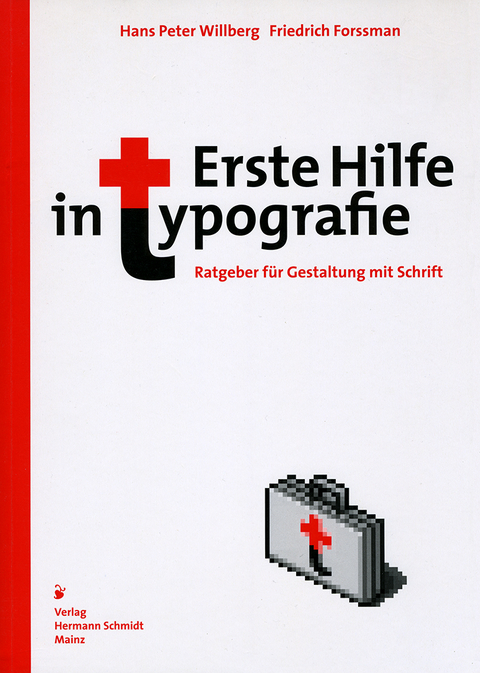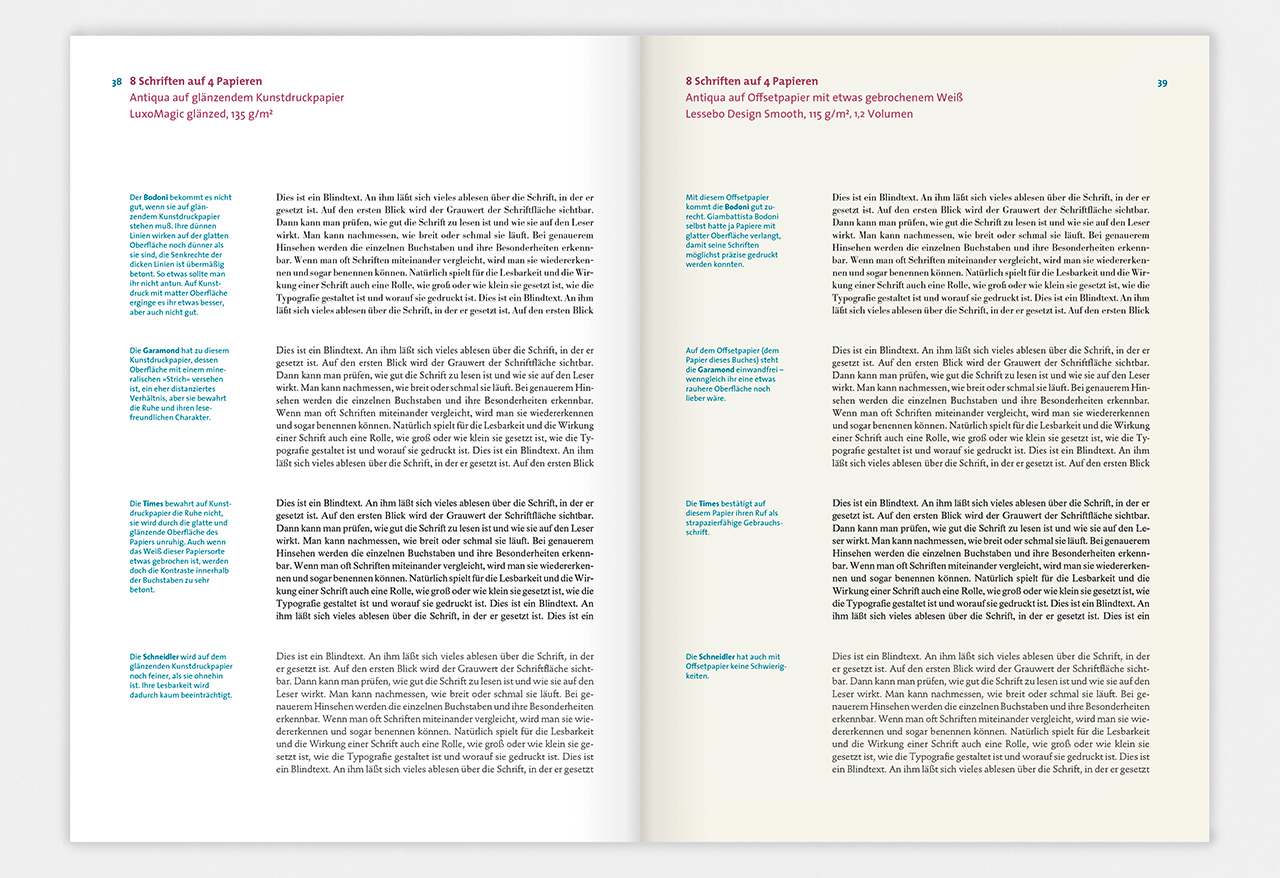
Erste Hilfe in Typografie
Ratgeber für Gestaltung mit Schrift
Jeder, der am Computer einen Text erfasst, gibt ihm eine Form. Bewusst, gekonnt, unbewusst oder ungekonnt, wir setzen ihn in Szene – und interpretieren ihn. Nicht immer – und vor allem nicht automatisch – zu seinem Wohl. Erste Hilfe in Typografie ist der erfolgreichste Typografie-Grundkurs. Der ideale Einstieg in die Welt der Gestaltung mit Text und Bild für angehende Profis ebenso wie für alle, die in ihrer schriftlichen Kommunikation den richtigen Ton treffen wollen.
Willberg und Forssman verstehen es, das Wesentliche allgemein verständlich zu formulieren. Von der Schriftwirkung geht die »Tour de Typo« über Lesbarkeit zum Unterscheiden von Schriften und zu Schriftmischungen. Weiter geht’s mit Wortzwischenräumen, Zeilenabstand, Inhalt und Satzbreite.
Dass die Papierwahl die Wirkung von Schrift beeinflusst, zeigen acht Schriften auf vier unterschiedlichen Papieren. Repro und Druck werden ebenso beleuchtet wie Block- und Flattersatz und typografische Betonungen. Die korrekte Behandlung von Ziffern und Zahlen sowie die beliebtesten Fehler runden den typografischen Parcours ab.